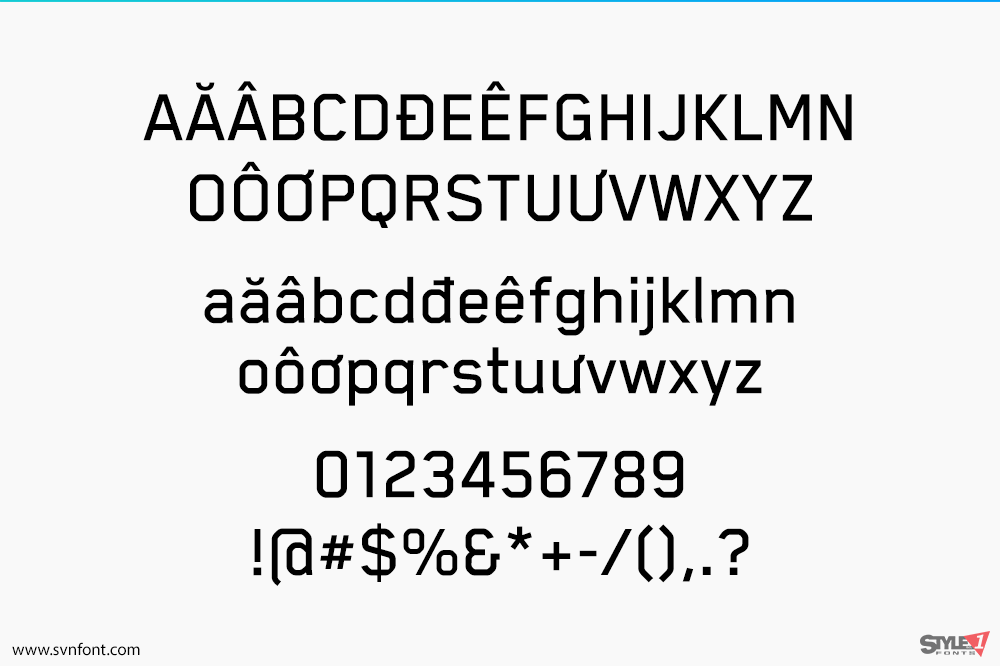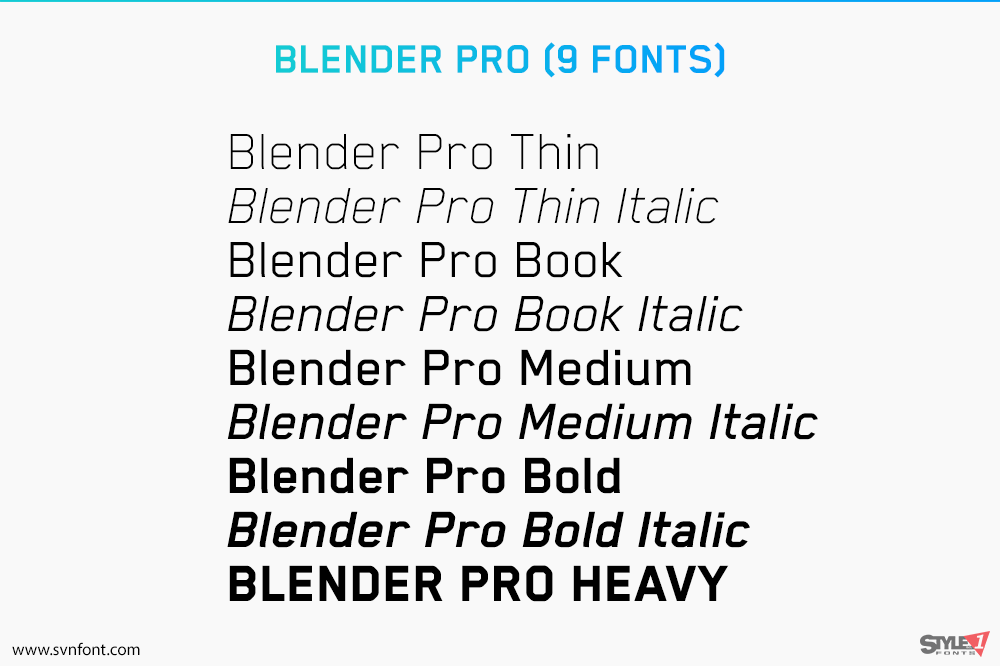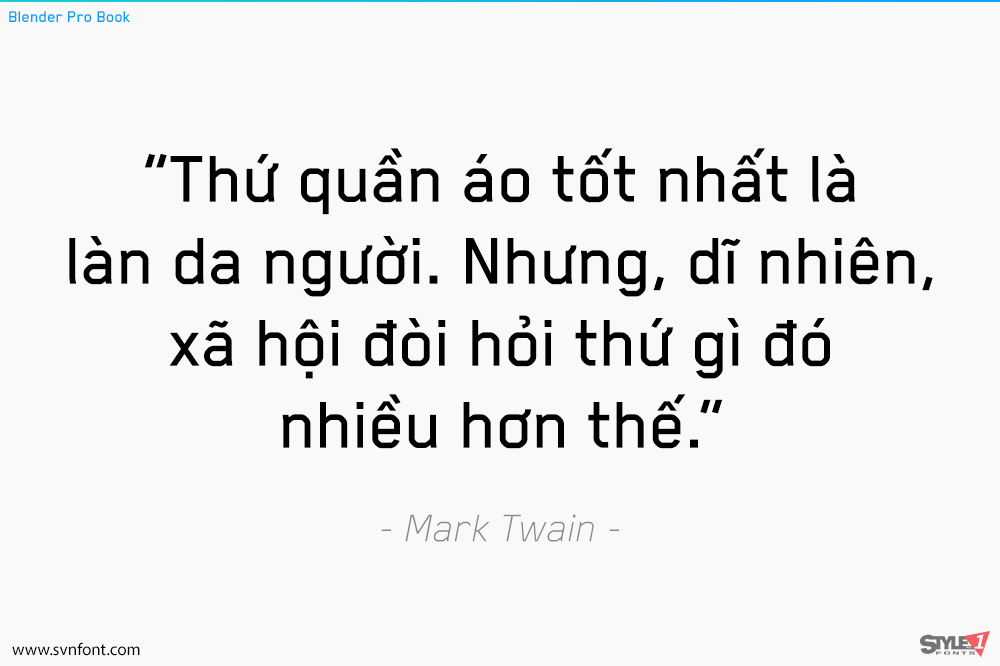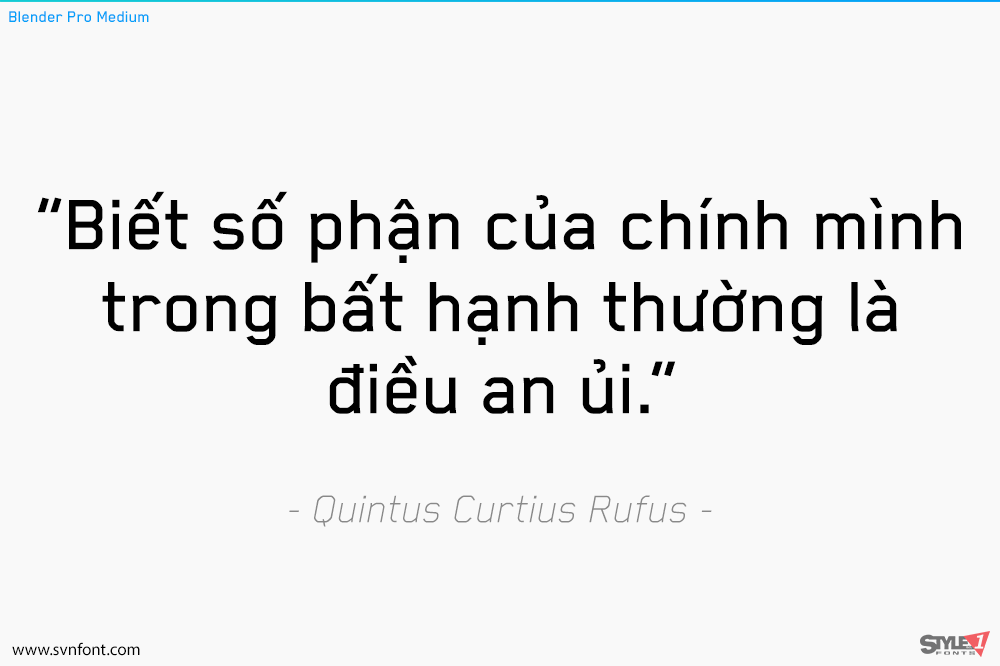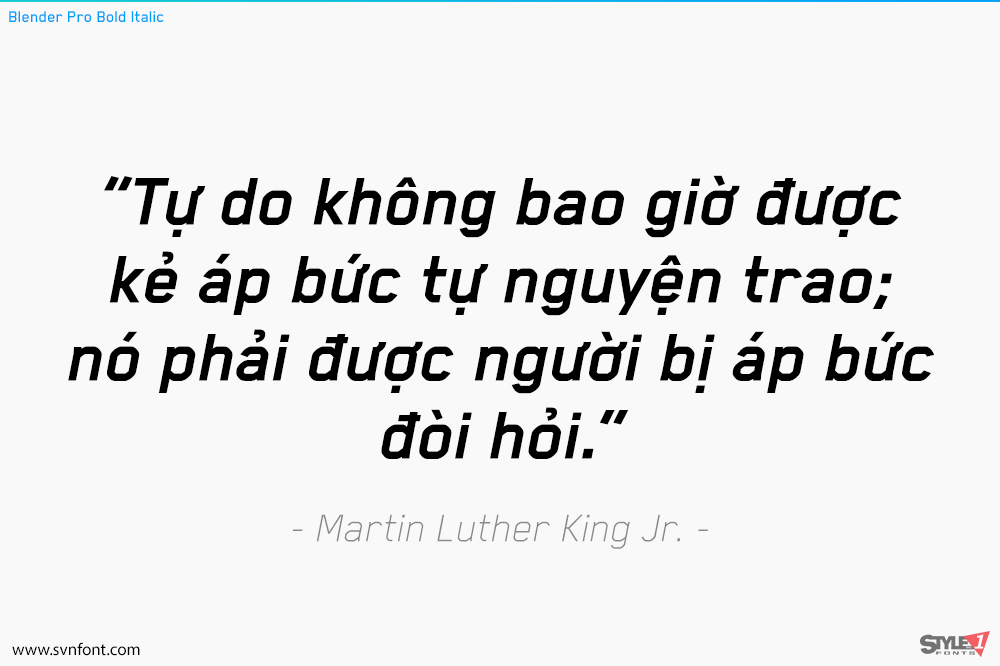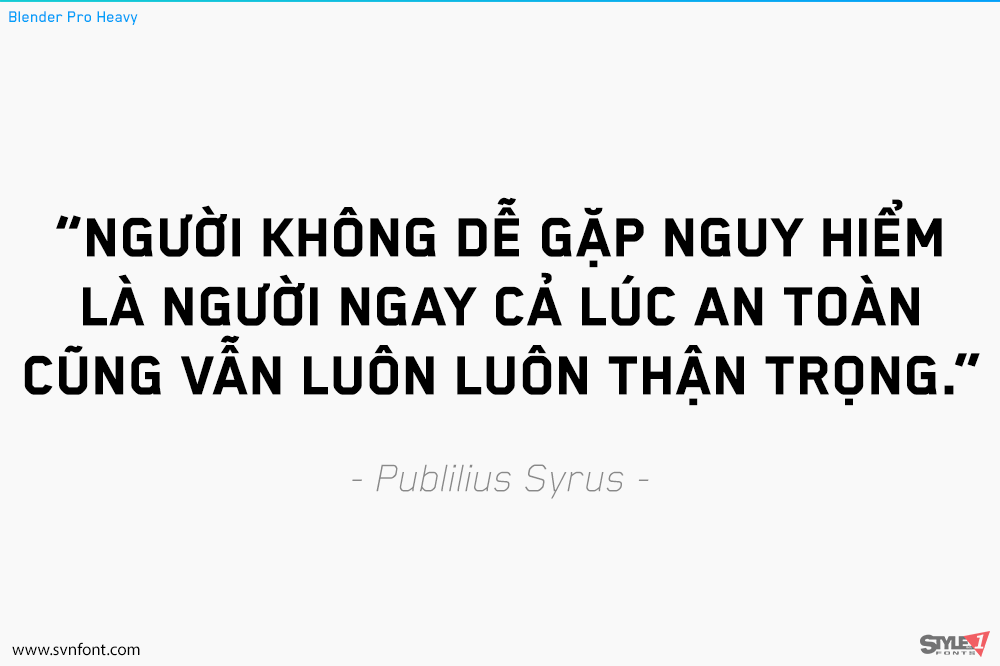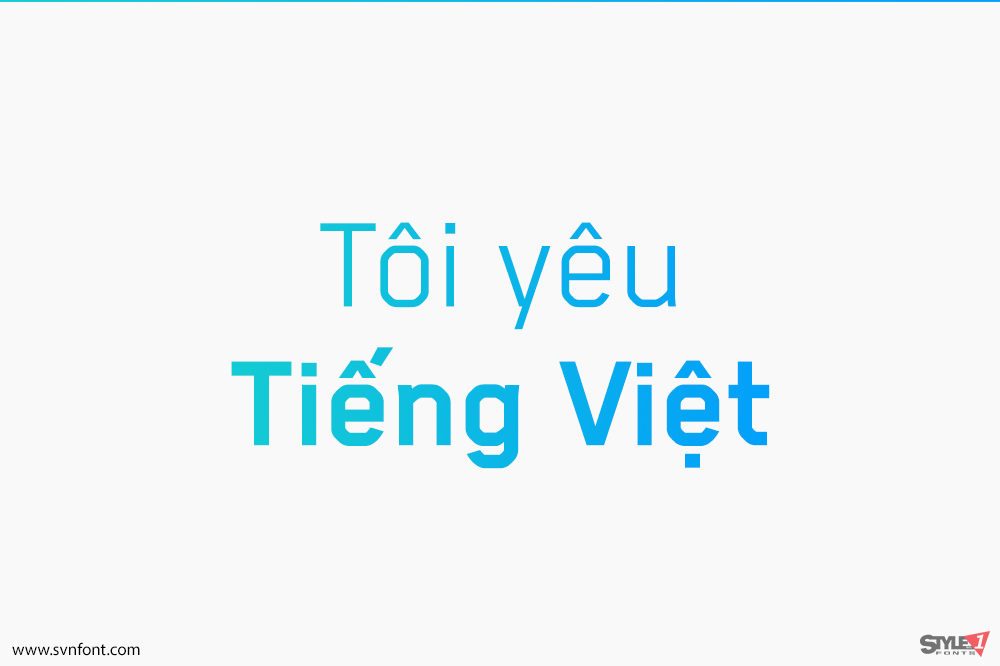
Trong ngôn ngữ học, “blending” (hòa trộn) có nghĩa là pha trộn các bộ phận, còn gọi là hình vị (morphemes), là những đơn vị nhỏ nhất có nghĩa về hình thức và nội dung. Các đơn vị nhỏ nhất trong phông chữ Blender được định nghĩa là các phân đoạn (segments) có được từ việc hòa trộn hai phông chữ. Các phân đoạn này được cắt ra từ những hình thức lai đã tạo ra và được lắp ráp lại, tái kết hợp thành các ký tự mới trên lưới cấu trúc cứng nhắc bên dưới. Phông chữ này tuân theo một nguyên tắc lý tính nhưng vẫn giữ được vẻ ngoài mềm mại một cách kín đáo nhờ các điều kiện hình thức của nó.
Nhà thiết kế: Nik Thoenen